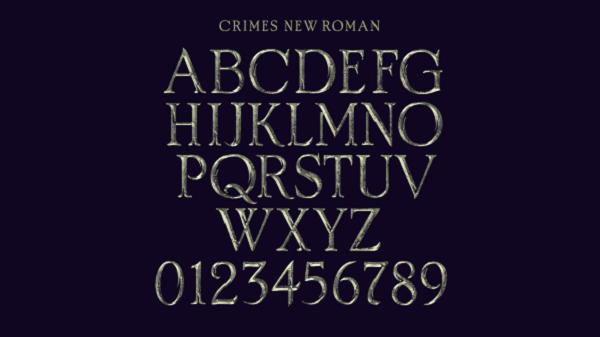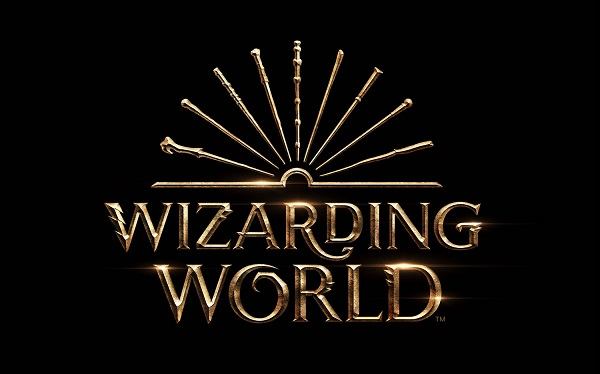
Nova tipografia de “Harry Potter” liga franquia ao mundo de “Animais Fantásticos”
Com o nome de Crimes New Roman, nova tipografia é inspirada nos elementos de "Harry Potter e as Relíquias da Morte"
A Warner Bros. juntou-se ao estúdio de design Pentagram para criar uma identidade visual que liga a série original de “Harry Potter” ao universo de “Animais Fantásticos”.
A nova tipografia leva o nome de Crimes New Roman. Já o logotipo foi inspirado em “Harry Potter e as Relíquias da Morte”
, sendo mais conhecido pelo público. A letra “I” remete à Elder Wand, a chamada “varinha das varinhas”, enquanto o “A” representa o manto da invisibilidade e o “G” remete à pedra da ressurreição.
Segundo Emily Oberman, parceira da Pentagram, a Warner Bros. prefere ter uma própria fonte que seja reconhecível pela marca, o que também ajuda outras agências que trabalham com a empresa a replicar materiais sempre iguais e identificáveis pelo público.